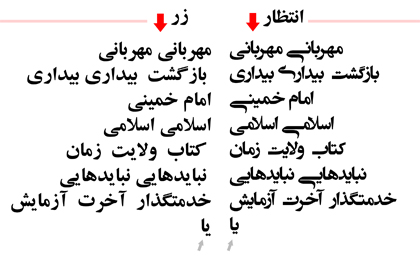
فونت انتظار
فونت انتظار / Entezar Font
فونت زیبای انتظار ، برای اولین بار در نوروز ۱۳۹۰ منتشر شد . این فونت از ایجاد تغییرات گسترده بر روی فونت زر تهیه شده است . کافی است این فونت را با فونت زر که یکی از رسمی‌ترین و پرکاربردترین فونت مورد استفاده در روزنامه‌ها و نشریه‌هاست ، مقایسه کنید تا زیبایی غیر قابل انکار آن را تحسین نمایید . شما می‌توانید در طراحی‌های خود ( پوستر ، بنر و … ) از این فونت زیبا استفاده نمایید .
قلم‌های انتظار و زر
مقایسه‌ فونت‌های انتظار و زر